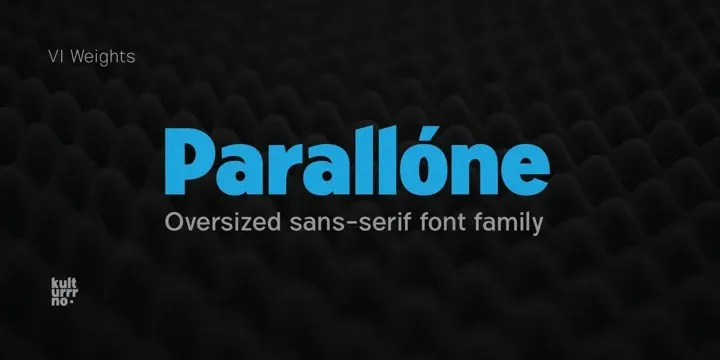
A Parallone Font Family é uma sans serif moderna que se destaca por sua elegância simples e versatilidade. Perfeita tanto para uso diário quanto para aplicativos profissionais, esta fonte é perfeita para diversas necessidades gráficas do dia a dia. Seja em uma capa de livro ou um texto sublinhado, este tipo deixa sua marca com precisão e clareza. É perfeito tanto para textos de destaque quanto para aplicações digitais que exigem formalidade. Seu design clean e limpo faz dele uma opção ideal para usar como fonte overlay em qualquer imagem de fundo ou texto formado, tornando-a um recurso indispensável para designers gráficos atentos aos detalhes.